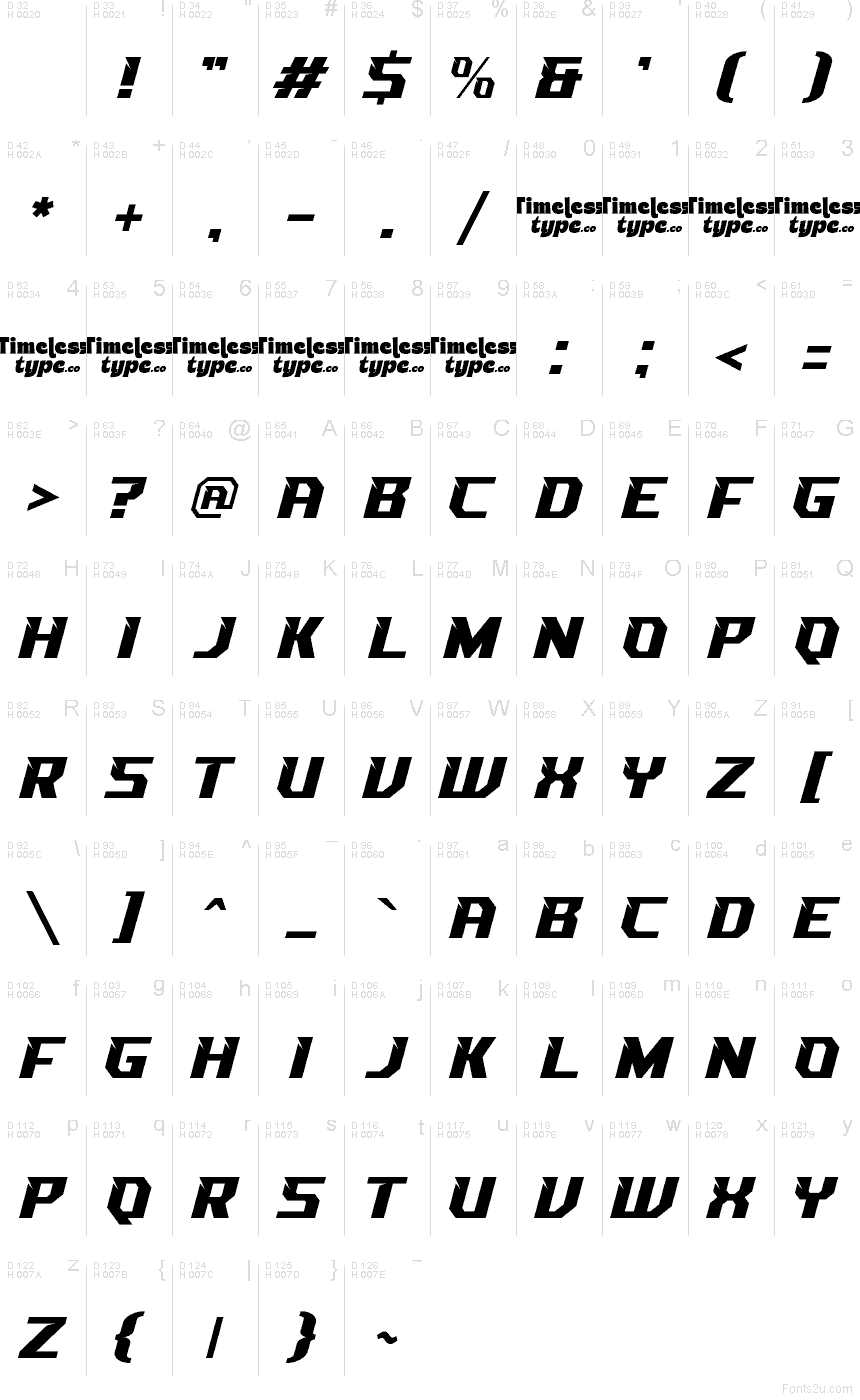
Sound Wave Racing od TimelessType je bezplatný techno display font s dravým, závodním charakterem. Velká písmena ztělesňují energii motorsportu díky ostrým diagonálním řezům, zkoseným rohům a robustním tvarům, které působí, jako by je vyformoval pohyb, nikoliv jako by byly navrženy pro neutralitu.
Díky tomu se přirozeně hodí na závodní plakáty, branding esportů, obaly alb, letáky akcí a titulky, kde musí krátký text vyzařovat skutečnou rychlost. Jako bezplatný font je také ideální pro loga, nadpisy a iniciály, protože písmena do sebe zapadají v těsném, agresivním rytmu, který působí jako ztělesněný pohyb.